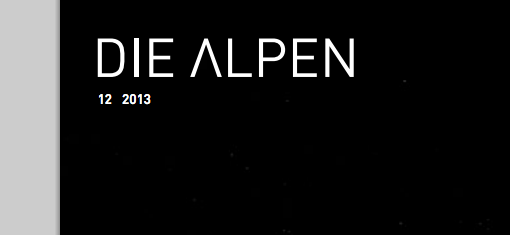
Schrift zum Thema Fels/Berg
Ich darf/muss die Gestaltung der Alpen Clubnachrichten übernehmen.
Fürs das Titelblatt suche ich eine Schrift die zum Thema Fels/Berg/Stein passt.
Auf dem Foto (das Foto ist nicht von super Qualität) eine Idee wie es aussehen kann.
Diese Steinmannli, (wie sagt ihr in D dazu?) sind das Vorgegebene Thema.
Die Schrift ist von meinem Vorgänger und gefällt mir nicht, zu rund.
@Kamuffel: Ich an Deiner Stelle würde keine Schrift wählen, die aussieht wie Stein oder Fels, weil ich das für einen solchen Schweizer Alpenclub zu verspielt und vordergründig finde.
Ich würde die Schweiz eher auf typografische Weise zelebrieren. Es gibt eine großartige Schweizer Typografie-Tradition, ein Füllhorn schöner Schriften, auf die man bei diesem Projekt zurückgreifen könnte. Vom Gefühl her würde ich auf eine klare, konstruierte Serifenlose setzen und vielleicht mal mit leichten und schweren Schnitten experimentieren, um den Gegensatz der Elemente darzustellen: Himmel und Erde, stabiler Fels und luftige Höhe, Natur und Kultur.
Alternativ könnte ich mir so eine Richtung wie von Phoibos vorgeschlagen vorstellen, allerdings dann vielleicht sogar eine eckigere, unangepasstere Slab-Serife. Ich meine mich zu erinnern, dass solche Schriften hier im Forum schon vorgestellt wurden, ich habe aber spontan keine Namen parat. Ich vermute, dass die geschätzten Kollegen R::bert und RobertMichael (und etliche andere Kollegen auch) da direkt einige Vorschläge aus dem Hut zaubern könnten.   :-)
OT: Ich habe gerade die Schweizer Steinschrift gefunden. Weiß einer der Kollegen zufällig, was es damit auf sich hat?
Wenn ich (als Nichtprofi) richtig verstanden habe geht die Schrift der Gesamtschweizer Zeitschrift des SAC in die besprochene Richtung?
PS: Welche Schrift ist das?
Schriften, die mir spontan in den Sinn kommen:
• Massif oder David Hadash
• Ode
• Mevum
• Amman
• Antithesis
• Vista
Außerdem würde ich mir auch mal die modernen Gebrochenen ansehen:
Je nach Gestaltung könnte wie Kathrin schon beschrieben als Kontrast auch eine klare Serifenlose gut funktionieren – ich würde vermutlich zu den spitzeren, geometrischen greifen:
Könnte man auch mal schauen, ob es da was passendes aus Schweizer Feder gibt. ;-)
Hey, prima! Die Schweizer Fibel-Schrift fehlte mit noch in der Sammlung. Anscheinend haben die Schweizer ja eine besondere Beziehung zu Steinen :-)
Mit der Scxhräg- Verbundene- oder Schnürlischrift hatte ich mir ja grade erste herumgeschlagen, und sie mit OpenType-Buchtabenverbindungen versehen.
In der Schule nannten wir die erste Schrift die wir lernten Steinschrift dann kam die Schnüerlischrift.
Das kann eine von vielen Sans Serif-Schriften sein, bei der für das Logo das V zum A gedreht wurde. Kommt öfter vor. Die Aeonis von Erik Faulhaber hat aber tatsächlich so was im Angebot, ein vordefiniertes Stylistic Set bietet auch ein »normales« A.
im gezeigten beispiel ist es meines erachtens eine modifizierte ff din:
Irgendwie lese ich das spontan immer als Lambda, und dann wird aus Aeonis Loeonis.
Daher kann es auch sein, dass hier gar nicht am A herumgeschnippelt wurde, sondern erinfach nur ΛLPEN geschrieben wurde
das nehme ich dir nicht ab, dass du – als muttersprachler einer sprache, die mit der lateinischen schrift geschrieben wird – nicht als allererstes automatisch ›DIE ALPEN‹ liest (wie vorgesehen) und erst dann in einem zweiten, viel bewussteren schritt noch wahrnimmst: ach, das modifizierte ›A‹ ist ja auch noch ein lambda. bei jemandem, der das griechische und das lateinische alphabet gleich flüssig liest, wäre es eventuell vorstellbar, dass derjenige womöglich den buchstaben falsch liest. aber selbst in diesem fall sorgt der sprachliche kontext (ein deutschsprachiges forum, in dem eine offensichtlich deutschsprachige schweizerische zeitschrift erwähnt wird) höchstwahrscheinlich dafür, dass die ›verwechslung‹ bloß ein nachgedanke bleibt (so wie mehrsprachige in anderen zusammenhängen auch sprachübergreifende mehrdeutigkeiten erkennen, ohne davon häufiger als in einzelfällen verwirrt zu werden).